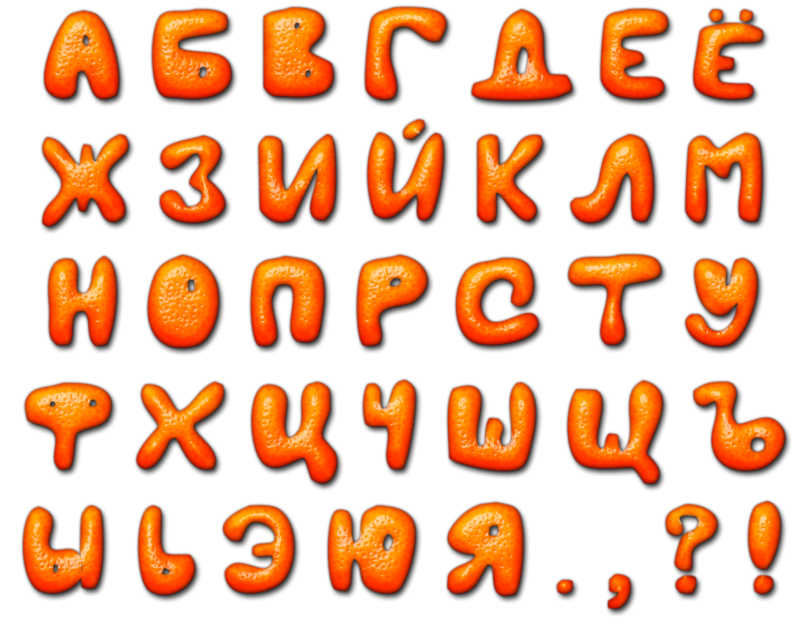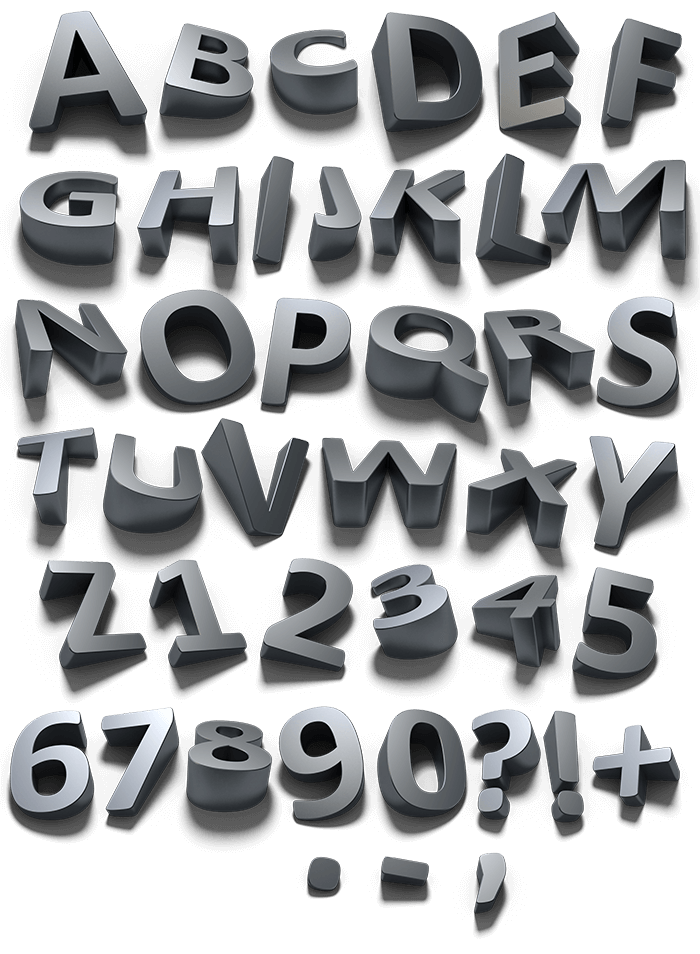
После этого буквы выпиливаются лобзиком.
Можно для ускорения выпиливания сбить гвоздиками два-
три слоя фанеры и вырезать сразу несколько экземпляров бук¬
вы. Выпиленные буквы зачищаются наждачной бумагой, затем,
если надо, раскрашиваются или бронзируются.
Наклеиваются буквы на основу по шаблону.
ОБЪЕМНЫЙ ШРИФТ
В современном оформительском искусстве широкое приме¬
нение находят объемные буквы. Они изготавливаются из самых
различных материалов — металла, дерева, всевозможных видов
пластмассы, пенопласта и др.
Объемный шрифт применяется при выполнении особенно
выразительных, броских, останавливающих внимание надписей.
Кроме объема и рельефа, соз¬
дающего светотень, выразитель¬
ность этих букв подчеркивается
также материалом, цветом букв
и фона, сочетанием их рельефа
с плоскостными надписями и
изображениями (рис. 189).
Белые рельефные буквы на
белом фоне, воспринимаемые
189. Объемная надпись только благодаря светотени,придают надписи особенно тор¬
жественный и эффектный вид.
Но такая надпись нуждается в специальном искусственном осве¬
щении, выявляющем ее рельефность. Обычное изменяющееся
дневное освещение может временами делать ее совсем неви¬
димой.
Хорошо разместить рельефные буквы на цветном фоне. Такая
надпись легко читается при любом освещении.
Объемные буквы могут и не прилегать плотно к плоскости
фона, а находиться на некотором расстоянии от него. Это рас¬
стояние создается или за счет рельефности фона или специаль¬
ных штырей, на которых крепятся буквы. Такой прием создает
Буквы очень значительного рельефа можно изготовить из
тонкого картона или чертежной бумаги (рис. 190). Такие буквы
в зависимости от их назначения и прочности материала могут
быть самой различной величины.
На листе прежде всего расчерчивается по возможности пол¬
ная развертка всех будущих граней буквы: лицевой — собствен-
но буквы, боковых и задних, приклеивающихся к плоскости.
других стационарных форм
КОЛОНН демонстрантов. Рис. 190. Изготовление объемных
Объемные буквы могут бУкв из бумаги
быть выпилены из фанеры.
Окрашенные или сохраняющие свой натуральный цвет, они
очень эффектны на всевозможных щитах и выставочных стен¬
дах, где их обычно используют для заголовков и основных над¬
писей и цитат.
Выпиливание таких букв начинается с внутрибуквенных про¬
светов. Шаблоном при выпиливании служат особенно тщательно
сделанные буквы.
ВЫЖИГАНИЕ ШРИФТА
Иногда возникает необходимость сделать надпись на дере¬
вянном изделии, изготовленном в кружке народного приклад¬
выжигания. Для этого необходим электровыжигатель — метал¬
лический штифт с деревянной рукояткой.
Штифт накаляетсяпосредством электрического тока напряжением 2—4 в. При
этом необходим такой трансформатор, который позволил бы
менять рабочее напряжение и регулировать температуру на¬
грева наконечника.
Соприкасаясь с поверхностью дерева, раскаленный штифт
оставляет обуглившийся след, окрашенный в зависимости от
продолжительности прижигания и степени нагрева штифта
Выжигать буквы нужно внимательно и осторожно, так как
допущенные при выжигании ошибки очень трудно поддаются
исправлению.
ну, заранее подготовленному на прозрачной кальке или промасленной
бумаге.
Перед тем как приступить к написанию шрифта, стекло тщательно
промывают с мылом. Затем на стол кладут чистую белую бумагу, на
нее—подготовленный шаблон. Чтобы вся надпись оказалась в обрат¬
ном, зеркальном изображении, прочитываемом справа налево, шаблон
кладут на бумагу лицевой стороной.
После этого его накрывают чи¬
не сдвинулось относительно шаблона, его скреп¬
ляют с ним по углам четырьмя капельками клея. а
Затем приступают к написанию шрифта.
Выполнить надпись на стекле можно двумя
способами. При первом способе сначала пишут¬
ся, то есть обводятся и закрашиваются, буквы,
а затем тонируется фон. При выполнении шриф- 5*
та контурные штрихи могут иметь большую дли¬
ну, чем следует (рис. 34, а). Их можно устра¬
нить после просыхания букв. Например, все Рис 34 Два способа
лишние штрихи или неровные их окончания работы на стекле
можно подчистить лезвием бритвы. После этого
стекло с написанным на нем шрифтом покрывается краской. Она на¬
будь цветную подкладку, то его, конечно, тонировать не следует. При
втором способе — работе на просвет (рис. 34, б) — контуры букв обво¬
дятся тонким концом шлиппера.
Цвет линий контура при этом долженсовпадать с цветом фона. После этого поверхность стекла закраши¬
вается, за исключением самих букв. Закраску фона следует начинать
с внутрибуквенных просветов и пробелов между буквами. При желании
- Готический шрифт. …
- Современная каллиграфия. …
- Надпись с засечками. …
- Шрифт без засечек. …
- Новые стили надписей.
Какие 5 основных шрифтов?
Существует пять основных классификаций шрифтов: с засечками, без засечек, рукописные, моноширинные и акцидентные. Как правило, шрифты с засечками и без засечек используются либо для основного текста, либо для заголовков (включая заголовки, логотипы и т.